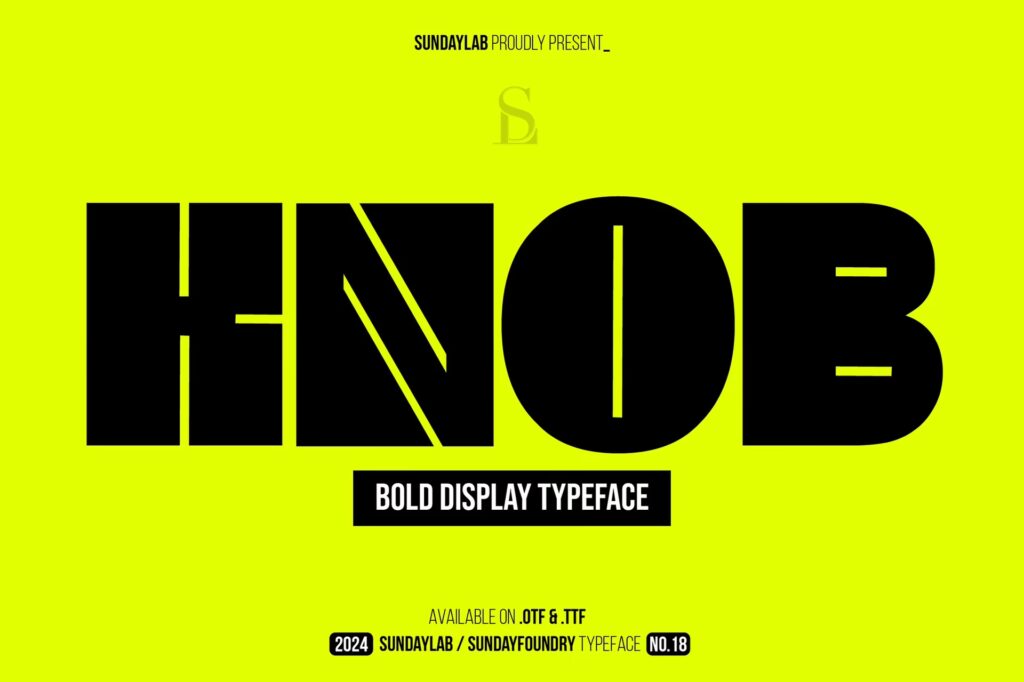
En el vasto universo del diseño gráfico y la comunicación visual, la elección de la tipografía es una de las decisiones más cruciales. Una fuente no solo transmite un mensaje, sino que también evoca emociones y define la personalidad de una marca. Dentro de este contexto, las fuentes cuadradas han ganado una inmensa popularidad por su capacidad para proyectar una imagen de modernidad, estabilidad y fuerza. Con sus líneas limpias, ángulos definidos y estructura geométrica, estas fuentes son la elección perfecta para proyectos que buscan un impacto visual claro y contundente.
Este artículo es una inmersión profunda en el mundo de las fuentes cuadradas. Exploraremos por qué son tan efectivas, presentaremos una selección curada de las mejores opciones disponibles —tanto gratuitas como premium— y te daremos las herramientas para que puedas encontrar e instalar la fuente ideal para tu próximo gran proyecto, ya sea un logotipo, un cartel o la identidad visual completa de una marca.
¿Por qué elegir una fuente cuadrada?
Las fuentes cuadradas, también conocidas como tipografías geométricas o de bloque, se caracterizan por sus formas angulares y proporciones equilibradas. Esta naturaleza estructurada las dota de una serie de ventajas que las hacen destacar en una amplia gama de aplicaciones.
- Modernidad y Tecnología: Su estética limpia y geométrica se asocia a menudo con el mundo digital, la tecnología, la ciencia ficción y el futurismo. Son ideales para startups tecnológicas, marcas de videojuegos o cualquier proyecto que quiera transmitir una sensación de innovación.
- Fuerza y Estabilidad: La base sólida de sus caracteres transmite una sensación de confianza, durabilidad y poder. Esto las hace perfectas para marcas de la industria automotriz, construcción, finanzas o deportes.
- Legibilidad e Impacto: Gracias a sus formas claras y definidas, son extremadamente legibles, especialmente en tamaños grandes. Son una opción fantástica para logotipos, titulares, carteles y cualquier diseño que necesite captar la atención de inmediato.
- Versatilidad: Aunque a menudo se asocian con un estilo audaz y masculino, existen innumerables variaciones. Podemos encontrar desde fuentes cuadradas elegantes y lujosas hasta opciones más lúdicas y creativas, lo que demuestra su increíble versatilidad.
Las Mejores Fuentes Cuadradas para tus Proyectos
El mercado está repleto de excelentes opciones. Para ayudarte a navegar por este mar de posibilidades, hemos recopilado una lista de algunas de las fuentes cuadradas más destacadas, cada una con su propia personalidad y uso ideal.
Si buscas un toque de exclusividad y sofisticación para tu marca, estas fuentes son una inversión que vale la pena considerar:
- Pluvix Luxury Font: Una tipografía elegante y audaz, diseñada para proyectos que exigen un acabado pulido y profesional. Es perfecta para marcas de lujo, invitaciones de alta gama o portadas de revistas.
- Zayan Luxury Font: Una serif sofisticada con formas limpias que equilibra el encanto clásico con el minimalismo moderno. Ideal para packaging de productos premium y branding exclusivo.
- Grizlie: Una fuente masculina y robusta con un estilo cuadrado que proyecta modernidad. Es una elección excelente para logotipos de equipos de e-sports, marcas deportivas o titulares con mucha fuerza.
- Frankerd: Captura la esencia del diseño industrial con una estética contemporánea y un borde mecánico. Funciona de maravilla en publicidad, señalización y packaging de productos con carácter.
Opciones Populares y Versátiles
Plataformas como FontSpace ofrecen un catálogo inmenso donde destacan algunas fuentes por su popularidad y calidad. Aquí tienes algunas de las favoritas de la comunidad:
- Big Space (de Nurf Designs): Como su nombre indica, es ideal para crear impacto en grandes espacios.
- Trench (de NimaType): Con un aire militar y estructurado, es perfecta para diseños con temática de acción.
- Kubots (de NimaType): Una fuente con un claro toque robótico y futurista.
- JACKPORT COLLEGE NCV (de the Fontry): Evoca el estilo clásico de las tipografías universitarias americanas, pero con un giro más cuadrado y contundente.
- Casanova Scotia (de Chequered Ink): Una opción con un estilo único y decorativo.
Fuentes Cuadradas Gratuitas: Un Vistazo a Micro Square
No siempre es necesario un gran presupuesto para acceder a tipografías de calidad. Existen excelentes opciones gratuitas, especialmente para proyectos personales o para probar conceptos. Un gran ejemplo es la fuente Micro Square.
Micro Square se describe como la fuente perfecta para todo tipo de diseños divertidos. Su encanto reside en su simplicidad y claridad. Sin embargo, es crucial entender sus condiciones de uso. La fuente Micro Square es gratuita únicamente para el conocimiento del estilo y para uso personal. Si deseas utilizarla en un proyecto comercial (un logo, un producto que se venderá, etc.), es indispensable contactar al autor para adquirir la licencia correspondiente. Esta es una práctica común en el mundo de las tipografías gratuitas.